常見的書法字體種類共有五種:篆書、隸書、草書、行書、楷書。
- 篆書:狹義的篆書指大篆與小篆,字形特色為筆畫勻稱。
- 隸書:筆畫特徵為蠶頭燕尾,字形寬扁,横筆長而直筆短。
- 草書:經常簡略文字結構,書寫快速,筆畫帶鉤連,易讀性較低。
- 行書:介於草書與楷書之間,兼具草書的奔放與楷書的工整。
- 楷書:筆畫平直,字形方正,容易書寫,易讀性高。
飄逸隨性的行書
一出來就很有存在感,像是鬼滅之刃裡會出現的招式名稱。
正風毛筆
- 不太會缺字 ✅
- 流暢、飄逸
正風毛筆這款字型是基於衡山毛筆フォント行書的開源中文字型,作者 MAX 透過程式增加不少文字與符號數,目前總字數已來到近 2 萬 4000 字。
正風毛筆共有 ExtraLight、Light、Regular、Medium、Bold 五種字重,原版字重放在 Regular,其他都是程式自動產生的字重,可能有筆畫過粗或過細的狀況。
青柳疎石フォント
- 容易缺字 ⚠️
- 恬淡、平實
青柳疎石フォント是日本書法家青柳疎石先生創作的字體,最大特色是若有似無的墨跡與自然日常的字形,看起來格外樸實。收錄字數包含 JIS 第 1・第 2 水準漢字,約有 6,000 多字。
英椎行書
- 容易缺字 ⚠️
- 隨性、日常
跟一般書法字型比起來,英椎行書算是字面較大的書法字型,書寫風格也比較像是生活中會看到的手寫字。收錄字數涵蓋到 JIS 第 2 水準漢字,約有 6,000 多字。
白舟行書教漢
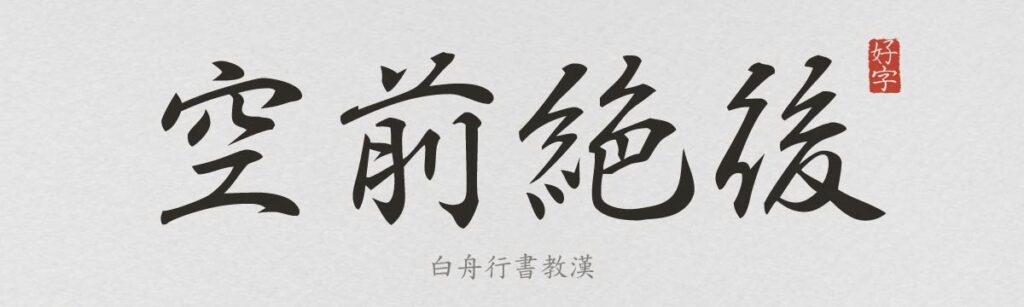
- 容易缺字 ⚠️
- 帥氣、氣勢
由日本字型公司「白舟書體」發行,白舟行書教漢筆畫流暢,自帶氣場。這間公司提供許多可供免費下載商用的書法字體,不過免費版的收錄漢字數僅包含日本的教育漢字,約 1,026 字。
演示夏行楷(簡體中文)
- 容易缺字 ⚠️
- 敦厚、堅毅
演示夏行楷是中國公眾號 Keynote 研究所人生哥發佈的字型,由北京中國書畫研究院研究員劉錫棟完成字稿,再交給 Keynote 研究所以電腦半自動化完成字型。
這款字是簡體字型,字形採用中國寫法,使用時要多加留意。收錄字數多以簡體字為主,繁體字雖有但容易缺字,推薦使用於標題或少數強調文字。
鐘齊志莽行書(簡體中文)
- 容易缺字 ⚠️
- 流動、舒展
鐘齊志莽行書的作者為書法家韋志莽,這款字型由他授權鐘齊字庫上傳 Google Fonts,字體風格令人想到晚清著名書畫藝術家吳昌碩。
收錄字數不詳,但不用對簡體字型抱有太大期待,排長文一定缺字。簡體字型的字形採用中國寫法標準,使用時要多加留意。
雲峰靜龍行書(簡體中文)
- 容易缺字 ⚠️
- 乾淨、舒暢
近年中國有越來越多字型廠商推出免費字體,這款雲峰靜龍行書就是中國雲峰字庫出品的第一套免費商用字型。跟上面的鐘齊志莽行書比起來,雲峰靜龍行書看起來更清爽,筆畫也較細。
簡體字型的字形採用中國寫法標準,使用時要多加留意。排繁體中文時很有可能會缺字。
雲峰飛雲體(簡體中文)
- 容易缺字 ⚠️
- 豪邁、大氣
雲峰飛雲體一樣是中國雲峰字庫的作品,是一款相當有標題份量感的字。簡體字型的字形採用中國寫法標準,使用時要多加留意。排繁體中文時很有可能會缺字。
Aa 劍豪體(簡體中文)
- 容易缺字 ⚠️
- 狂放、霸氣
字如其名,Aa 劍豪體看起來就像個劍客正在揮舞刀劍(劍豪這個音倒是很有親切感)。Aa 劍豪體是中國 Aa 字庫發佈的首款免費可商用字型。筆畫末端的爪勾讓字看起來如鷹爪般有力,轉折處尖銳突出,形狀特別剛硬鋒利。
簡體字型的字形採用中國寫法標準,使用時要多加留意。排繁體中文時很有可能會缺字。
ジンへな墨流 – RCF/RDF
- 容易缺字 ⚠️
- 質樸、自然
ジンへな墨流是日本網站 ZIN Font(ジンフォント)發佈的字型,這個網站專門販售看起來很彆腳的手寫字。這款字不知為何有種佛家感,向內塌陷的造型跟厚重的筆畫十分特殊。
ジンへな墨流有 RCF 跟 RDF 兩種樣式,主要差別在於大小及粗細,字形寫法似乎也有微妙的不同。
率性奔放的草書
有時候就是想要讓中文這種方塊字,看起來更抽象、藝術、有機一點。
草書
- 不太會缺字 ✅
- 藝術、乾淨
草書(狂草)是 mikhailcai 在中國百度貼吧發佈的自製免費字型,涵蓋 1 萬 7,000 多字(四書五經、聊齋等),全繁體字形。實測算是比較少缺字的書法字型,推薦給喜歡草書的你。
白舟草書教漢
- 容易缺字 ⚠️
- 奔放、不羈
由日本字型公司「白舟書體」發行,白舟草書教漢保留了字型的規矩與書法的行氣,在較大的字面中展現草書狂放的魅力。這間公司提供許多可供免費下載商用的書法字體,不過免費版的收錄漢字數僅包含日本的教育漢字,約 1,026 字。
鐘齊流江毛草(簡體中文)
- 容易缺字 ⚠️
- 瀟灑、圓潤
鐘齊流江毛草是 Google Fonts 上的免費開源字型,中文部分由書法家 Liu Zhengjiang 寫成,表現出文字的流動感。相較上面的草書,鐘齊流江毛草的運筆更隨性,文字高低錯落,表現出不一樣的動感。
衡山毛筆フォント草書
- 容易缺字 ⚠️
- 纖細、率性
衡山毛筆フォント草書是日本書法家青柳衡山的作品,保留了高速運筆下產生的飛白,視覺效果更加自然,較細的筆畫則塑造了文字的輕盈感。收錄字數包含 JIS 第 1・第 2 水準漢字,約有 6,000 多字。